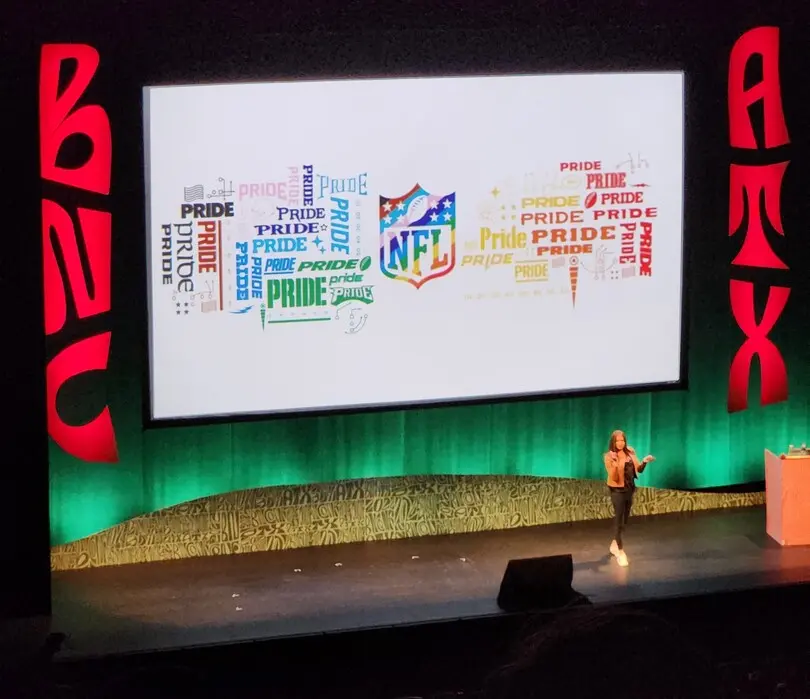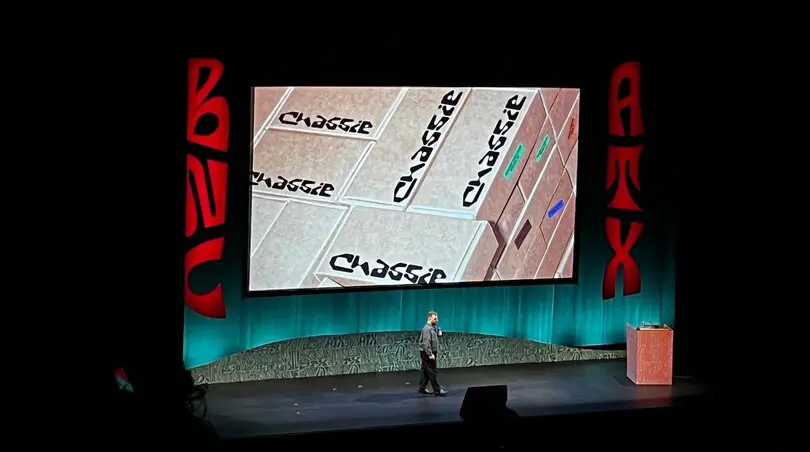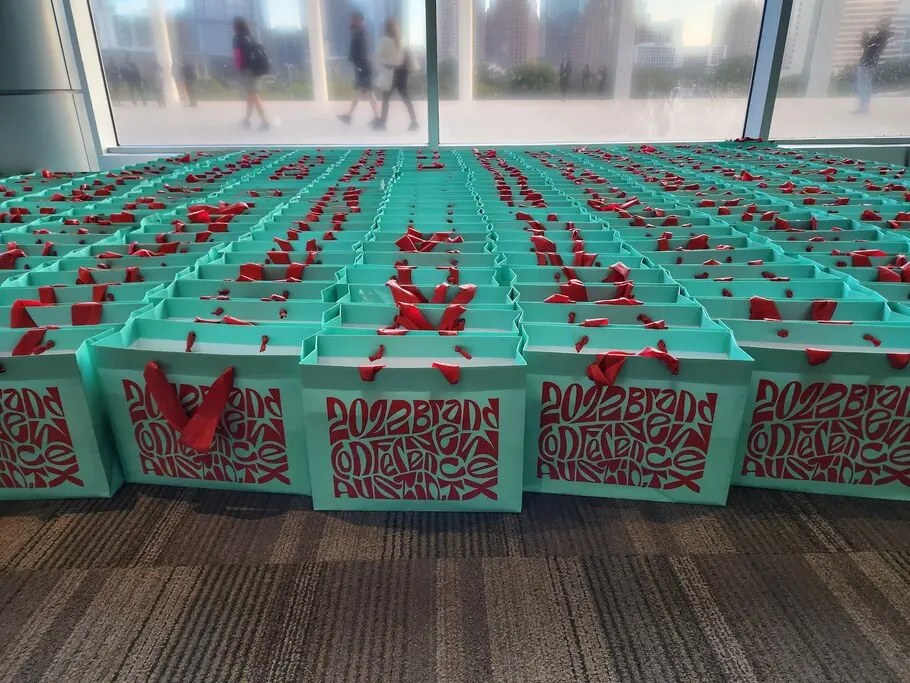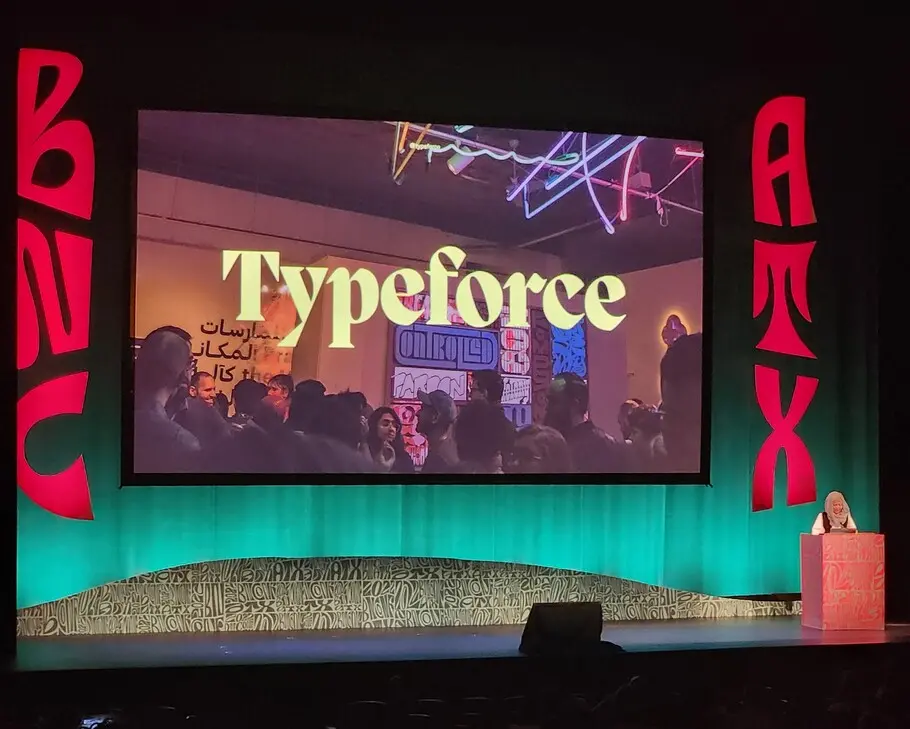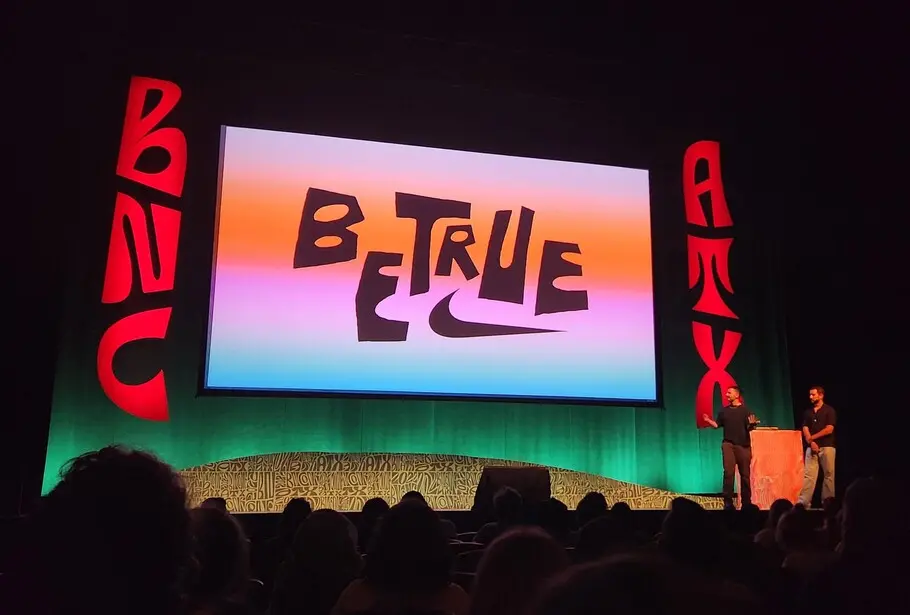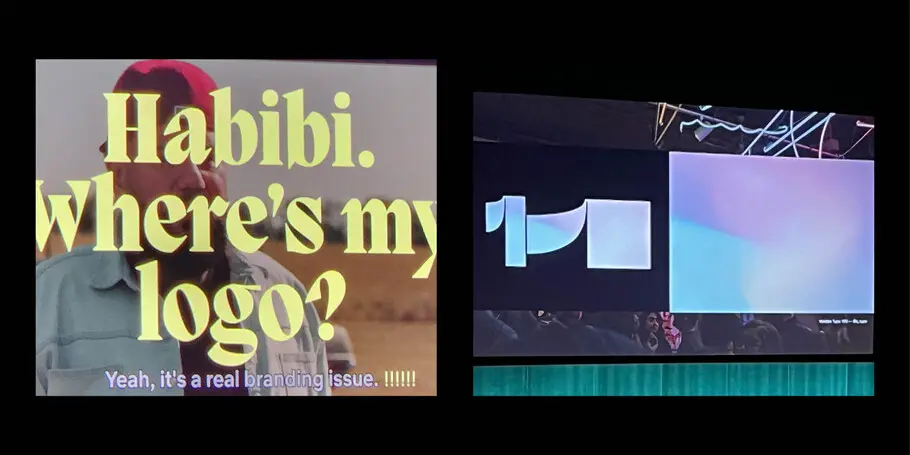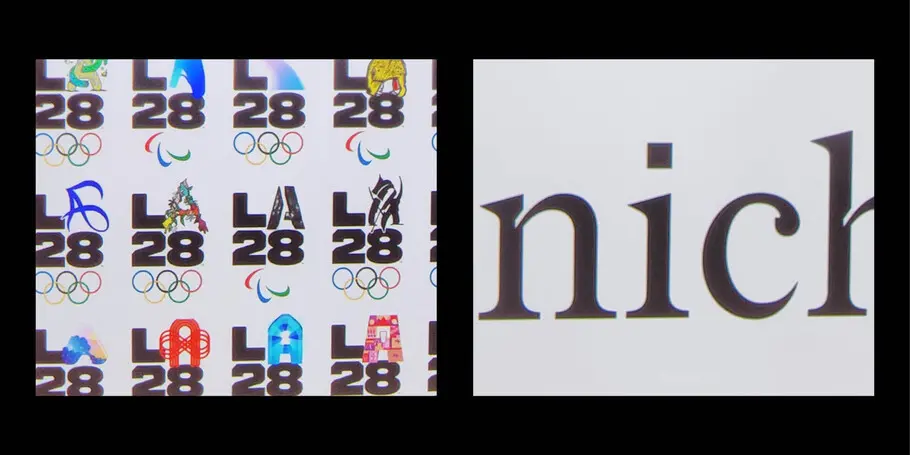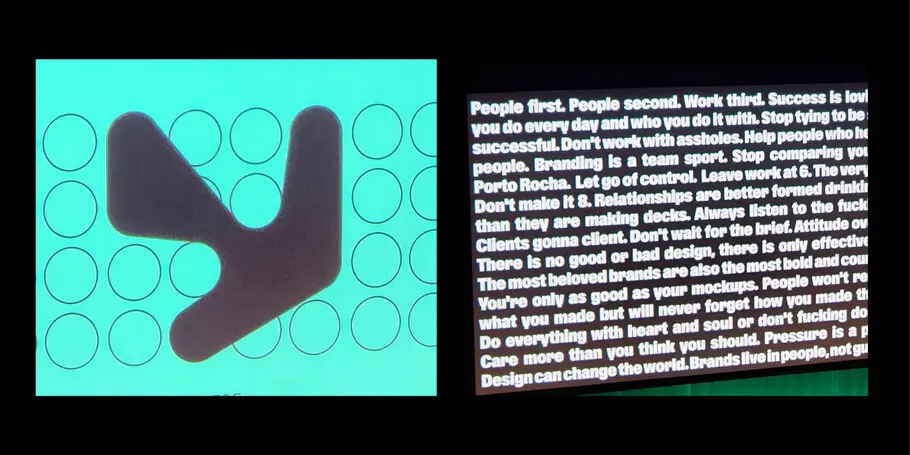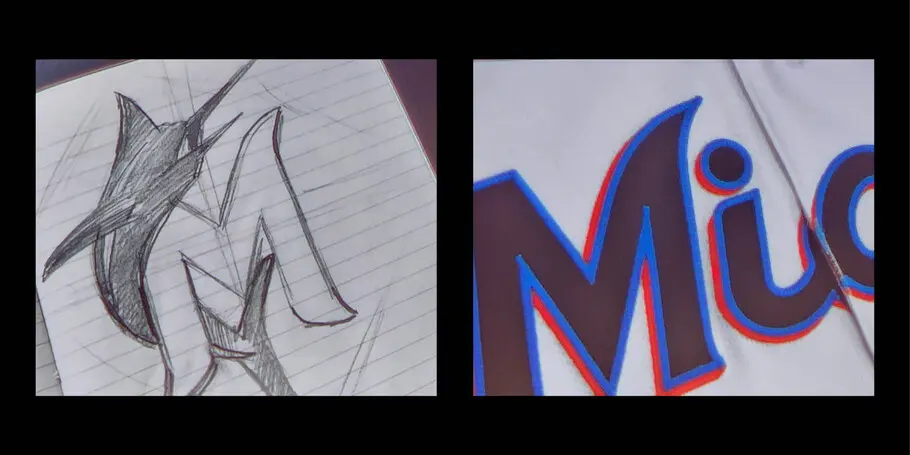
Fünf Mitbringsel von der Brand New Conference.
Wie viele andere waren auch wir dieses Jahr glücklich darüber, endlich wieder an einer Brand New Conference teilzunehmen, die von unseren Freunden bei UnderConsideration ausgerichtet wird. Es war ein gutes Gefühl, einige der einflussreichsten Persönlichkeiten aus der Design- und Markenwelt zu treffen und fesselnde Präsentationen, wunderbare Projekte und natürlich großartige Schriften zu erleben. Nachfolgend ein paar Erkenntnisse, die wir aus Austin, Texas, mitgenommen haben.
1. Marken werden gemacht und rebranded, …
Ein Muster, das uns in vielen Vorträgen am ersten Tag begegnete, war das Konzept der lebenden, dynamischen Identitäten, die ständig neu konzipiert, aktualisiert und sogar von der Crowd mitgestaltet werden – und das über lange Zeiträume.
Nermin Moufti, Kreativdirektorin, Strategin und Mitbegründerin von Field of Practice, stellte die Entwicklung der Identität von Typeforce vor, einer Ausstellung von Schriftkunst aus Chicago und Umgebung, die sie kuratiert. Die visuelle Identität wird bei jeder Veranstaltung neu gestaltet.
wieder verschwindet. “
Nermin Moufti.
Felipe Rocha, Gründer und Kreativdirektor von PORTO ROCHA, hatte eine ähnliche Perspektive auf das Design seiner Agentur für die Be True Kampagne von Nike.
Umgestalten gemacht wurde. “
Felipe Rocha.
2. Seid mutig.
Eine weitere durchgehende Linie war die Idee der großen, mutigen Marke. Ob sie mit experimentellen Schriften, frechen Botschaften oder raubeinigen TikToks an die Grenzen gehen: Viele Rednerinnen und Redner sprachen davon, wie wichtig es sei, Haltung zu zeigen und Risiken einzugehen.
Diese Forderung zog sich durch die gesamte Präsentation von Alex Center und durch alle von ihm gezeigten Arbeiten. Der in Brooklyn ansässige Designer und Gründer der preisgekrönten Markenagentur CENTER hebt sich mit seiner Arbeit für Chassie, einer in der Bronx ansässigen Möbelmanufaktur, von anderen Möbelmarken vor allem durch die wilde Typografie ab: ein anschauliches Beispiel für den „Organic Mod“ Stil, den wir in unserem 2022 trends report ausführlich darstellen („Siri: spiele Aphex Twin“).
“Die beliebtesten Marken sind die beherzten und die mutigen”– Alex Center
Nadya Okamoto, die 24-jährige Mitbegründerin von August, einer Lifestyle Marke für Menstruationsprodukte und mit einem selbstbewussten Verständnis für der weiblichen Periode, veröffentlichte einige Wochen lang täglich mehr als 50 TikToks, die sie auf der Grundlage ihrer Leistung optimierte.
etwas nicht funktioniert, lassen wir es einfach sein.
“
Nadya Okamoto.
3. Gute Arbeit kommt von glücklichen Menschen.
Es war ermutigend zu hören, dass mehrere Gründer der Work-Life-Balance eine hohe Priorität einräumen, in einer Branche, die für lange Arbeitszeiten bekannt ist und nicht selten die Selbstfürsorge zugunsten von eiligen Pitches oder Rationalisierungen hintanstellt.
Alex Center verlas vor einem jubelnden Publikum ein Manifest, in dem es unter anderem hieß: „Zuerst die Menschen, dann die Menschen, und dann die Arbeit … Verlasse deinen Arbeitsplatz 18:00, spätestens 19:00. Bitte nicht um 20:00.“
Als Nadya Okamoto gefragt wurde, wie sie es schafft, ihr eigenes Unternehmen zu führen, Vorträge zu halten, Zeit für Social Media zu haben und vieles mehr, antwortete die frisch gebackene Harvard-Absolventin nur: „Ich schlafe jede Nacht 10 Stunden.“
Ein weiterer Höhepunkt war die Präsentation von PORTO ROCHA, ein New Yorker Designstudio, das kreative und strategische Arbeiten entwickelt, die sich intensiv mit der Welt, in der wir leben, auseinandersetzen. Ihr neuer Report Design Threads (Designgedanken), der die Branche als Ganzes betrachtet und schwierige Fragen stellt, greift auch Themen wie Work-Life Balance und Burnout auf. Um den Bericht fertig zu stellen, hat das Team alle kommerziellen Projekte für eine Woche zurückgestellt, damit man sich ganz auf die Forschung konzentrieren konnte. Als sie die Besucher fragten, welches Emoji für sie das Jahr 2022 repräsentiere, sagte die Mehrheit „Schmelzendes Gesicht“ 🫠 , wegen der aktuellen Herausforderungen, denen Designerinnen und Designer ausgesetzt sind.
würde ich mein Büro nicht mehr verlassen. Es ist nicht mehr 9 to 5, sondern 9 to 12 … pm “
PORTO ROCHAs Design Threads.
4. Sei inklusiv, nicht performativ.
Wir befinden uns im Jahr 2022. Wissen Sie, wie es um Ihre DE&I-Situation (Diversity, Equity, Inclusion) bestellt ist? In den letzten Jahren haben wir beobachtet, dass Marken inklusiver werden möchten. Einige waren für ein paar Tage bei den Christopher Street Days dabei, andere ließen es etwas weniger bunt angehen, um über echte Veränderungen in ihrem Unternehmen nachzudenken.
PORTO ROCHA, gegründet von zwei queeren Latinos, präsentierte fünf essenzielle Ziele, auf die sie hinarbeiten und die eng mit Inklusion und Vielfalt verbunden sind.
Wir wollen, dass Designerinnen und Designer bei unseren Projekten mitentscheiden.
Wir wollen Marken mit Menschen und Kulturen auf sinnvolle Weise verbinden.
Wir wollen die gesunde Balance finden zwischen:
Design & Kultur und Geschäft & Strategie
Handwerk und Wachstum
5. Alles beginnt mit Schrift.
Wir sind zwar vorbelastet, aber wir waren begeistert, wie viele der Präsentationen von Projekten, Identitäten und Kampagnen mit einem Handlettering, mit Buchstabenskizzen, Inspirationen von Straßenschildern oder anderen typografische Preziosen begannen. Freuen Sie sich auf einen Beitrag über die Brand New Conference, der sich ausschließlich dem Thema Schrift widmet.